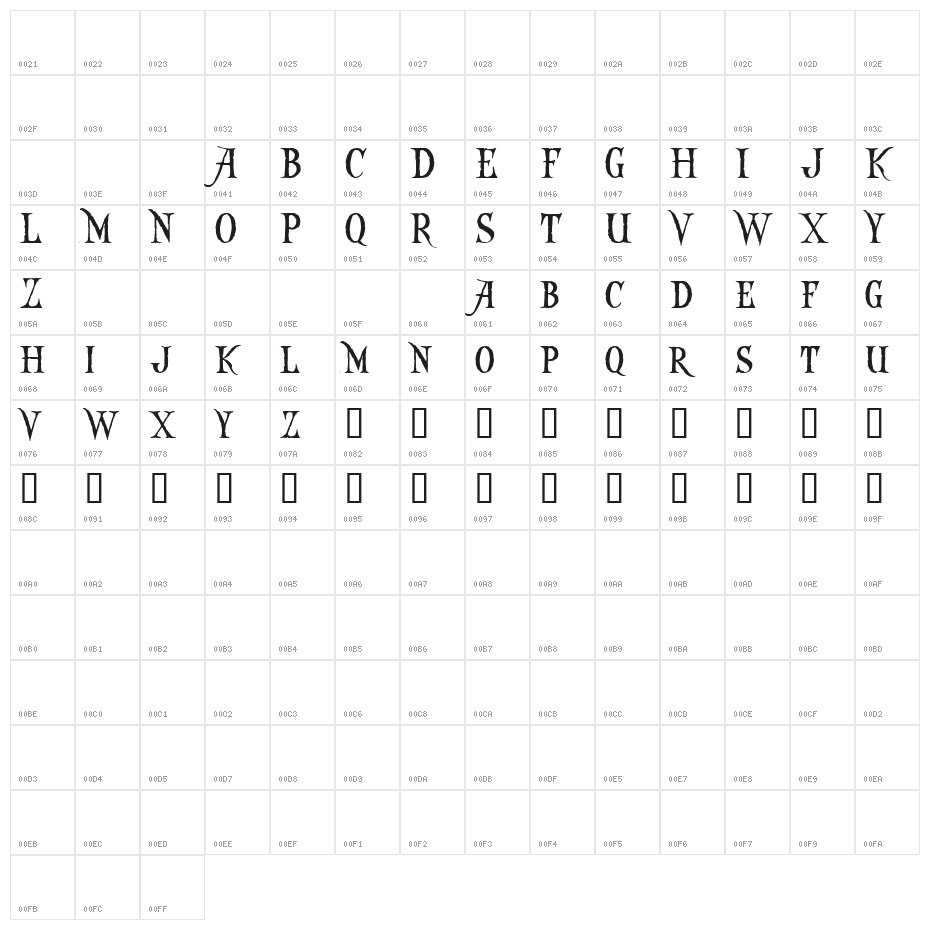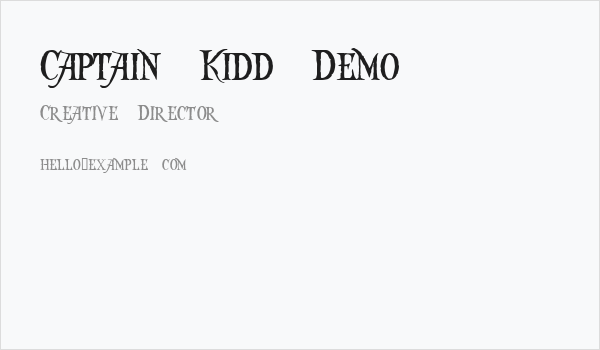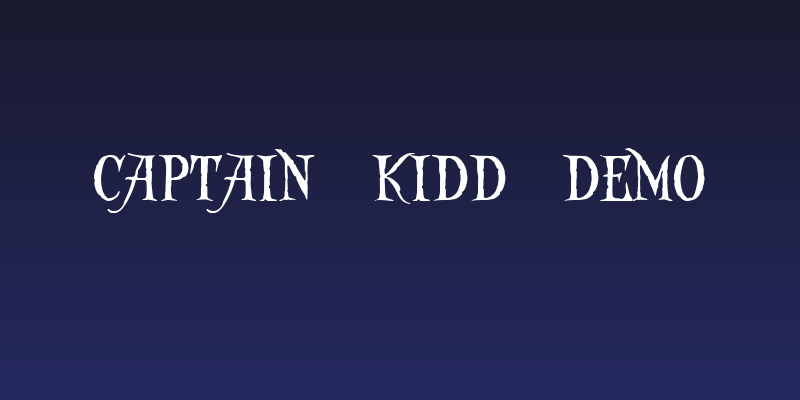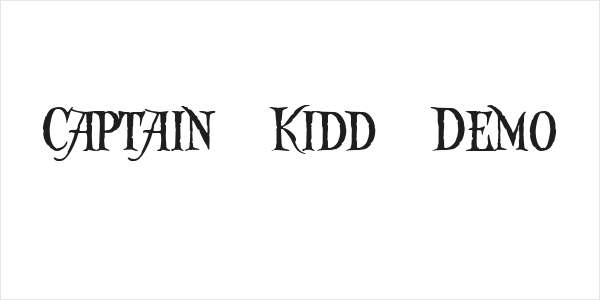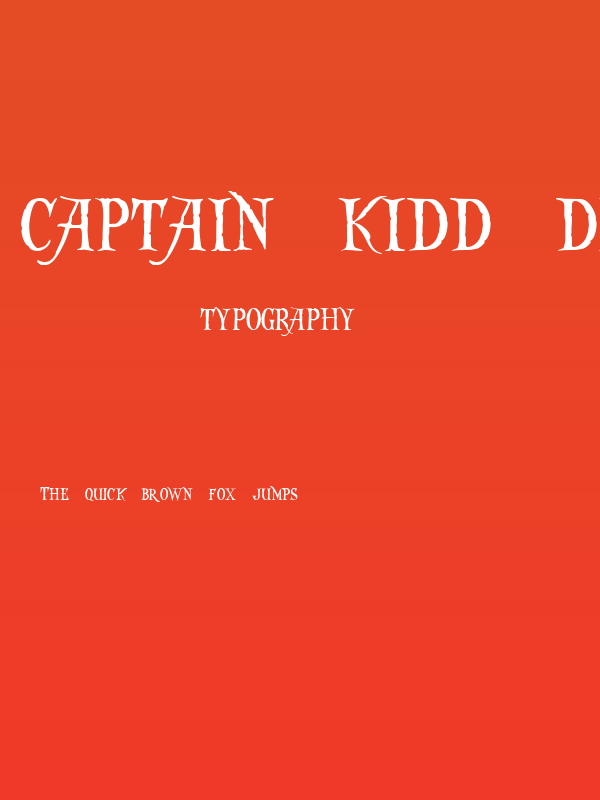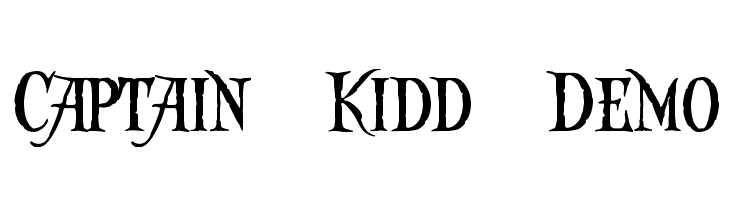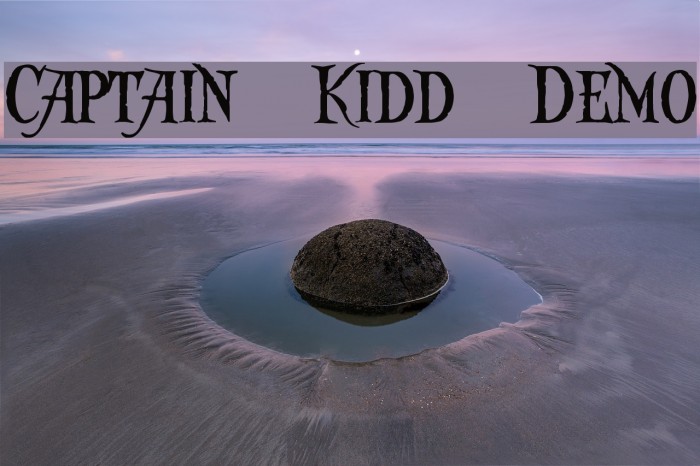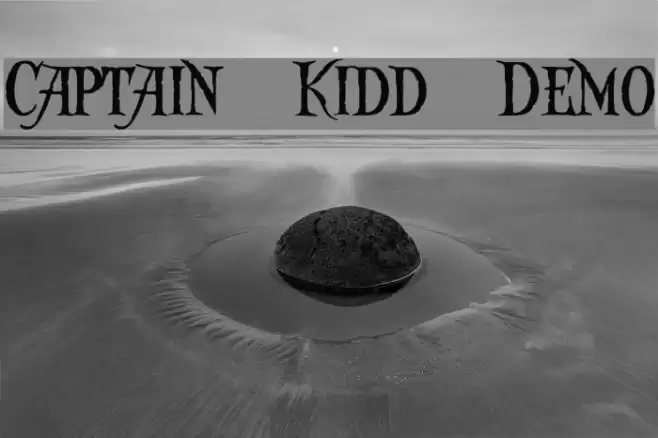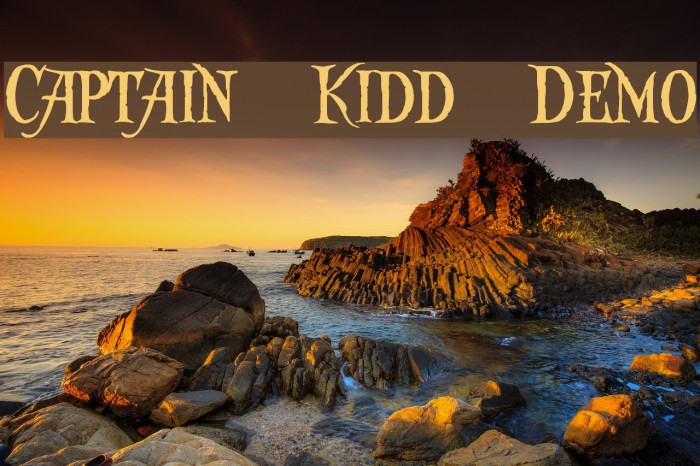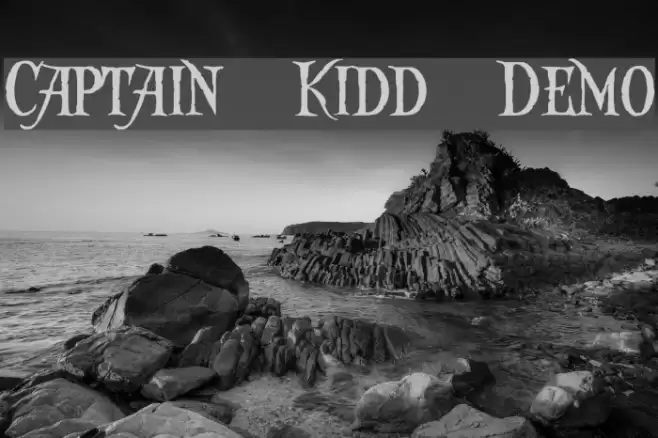
Captain Kidd Demo Font
Fonts by The Scriptorium - Dave Nalle
| Progetti proposti | Ideal for pirate-themed events, adventure book covers, themed restaurant menus, and dramatic poster designs. |